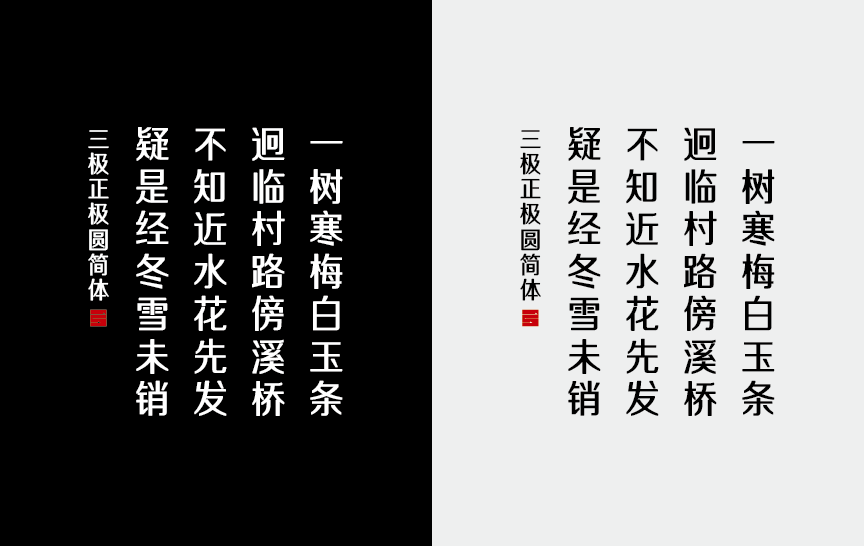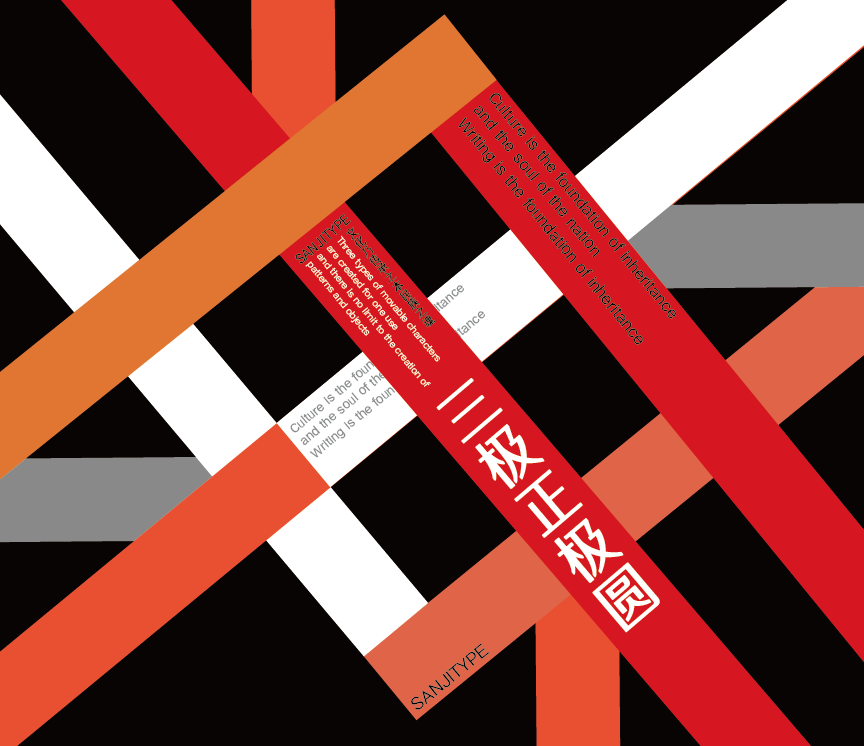
字体名称:三极正典圆简体
设计师:王荣诚
三极正典圆简体作品整体风格鲜明大气,字体结构有意偏窄纤瘦,笔画平直收笔圆弧彰显优雅、圆润饱满,竖粗横细,撇捺镜像对称稳健。它的灵感来源于黑体,又富有变化,给人婉转柔和的气质。视觉效果简洁易识别,实用性强。本作品适用于传统印刷媒介的标题与正文排版、各类屏幕显示及影视字幕等。